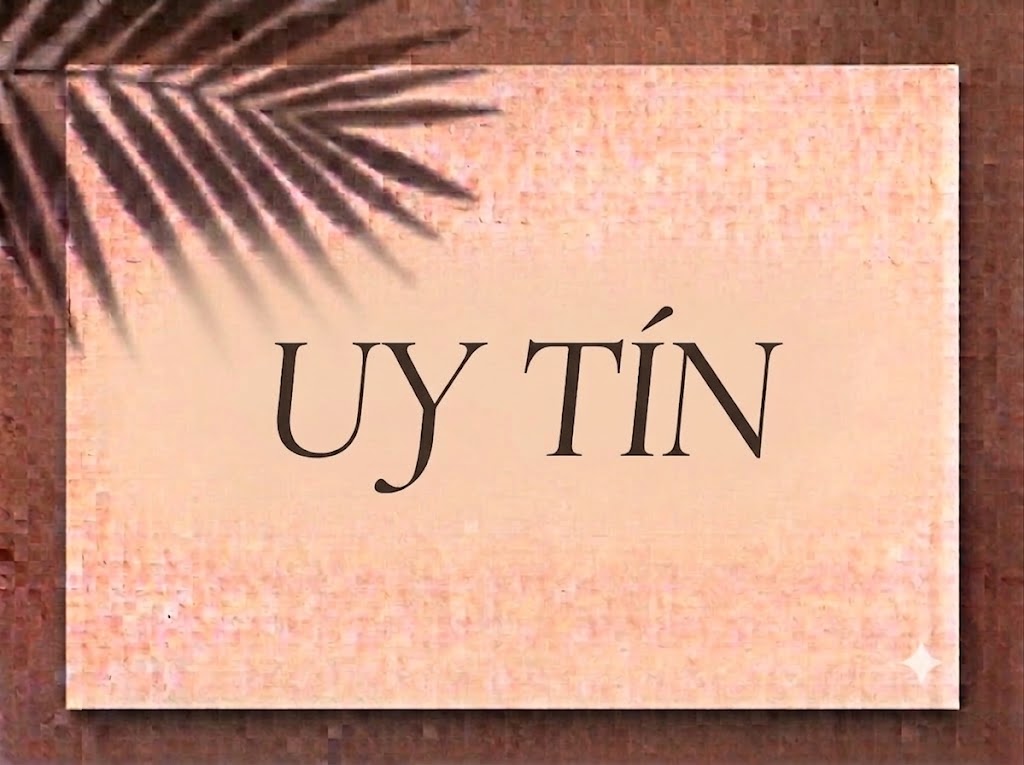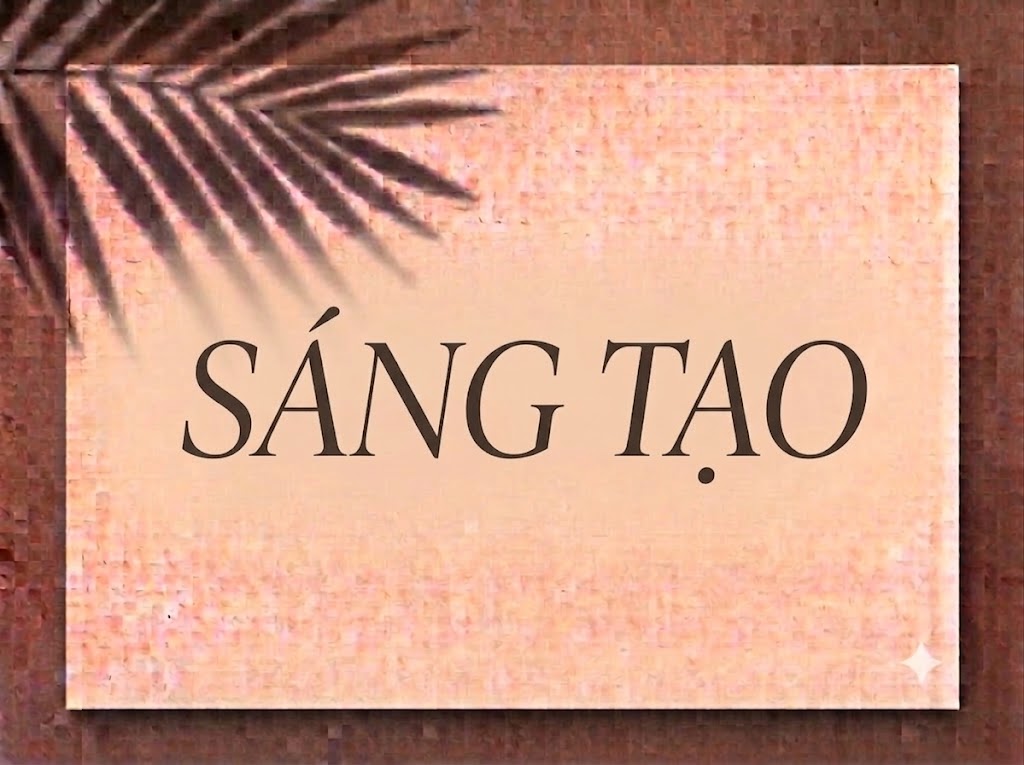
1FTV VIP Beauty Rovesa
Trong ngành thiết kế đồ họa cao cấp, các ấn phẩm thuộc lĩnh vực làm đẹp, spa, mỹ phẩm hay thời trang luôn đòi hỏi những phông chữ Serif sở hữu vẻ đẹp kiêu sa và đường nét tinh tế. Một tiêu đề được tạo hình đắt giá không chỉ giúp truyền tải thông điệp ngắn gọn mà còn ngay lập tức định vị thương hiệu ở phân khúc cao cấp.
Nếu bạn đang tìm kiếm một phông chữ hiển thị mang tinh thần sang trọng, kiều diễm với những nét uốn lượn mềm mại cho bìa tạp chí, logo spa hay tiêu đề video ngắn, font 1FTV VIP Beauty Rovesa chính là sự lựa chọn không thể bỏ qua.
Giới thiệu về font 1FTV VIP Beauty Rovesa
Font 1FTV VIP Beauty Rovesa là bộ chữ hiển thị có chân (serif display) mang phong cách tân cổ điển thanh lịch, nổi bật với sự kết hợp hài hòa giữa cấu trúc chữ Serif chuẩn mực và nét uốn lượn đầy tính nghệ thuật:
Tên phông chữ: 1FTV VIP Beauty Rovesa
Được tối ưu chỉn chu về mặt kỹ thuật, phông chữ đem lại khả năng hiển thị mượt mà trên mọi độ phân giải màn hình. Bạn có thể tự tin phóng lớn chữ trên các ứng dụng đồ họa chuyên nghiệp hay phần mềm dựng phim mà không lo gặp tình trạng vỡ nét hay răng cưa.
Đặc điểm nổi bật của phong cách thiết kế VIP Beauty Rovesa
Sức hút thị giác của font 1FTV VIP Beauty Rovesa đến từ vẻ đẹp mềm mại, quyến rũ cùng độ tương phản thanh đậm kịch tính:
Độ tương phản nét cực hạn: Sự chênh lệch rõ rệt giữa các cột dọc vững chãi và nét ngang mỏng nhẹ mang lại chiều sâu nghệ thuật, gợi liên tưởng đến trang bìa của các tạp chí thời trang và mỹ phẩm xa xỉ.
Nét biến điệu kiều diễm: Điểm nhấn đắt giá của phông chữ nằm ở các đường nét bo cong mềm mại ở các ký tự như e, g, f, a, T. Các chi tiết nét gạch ngang mảnh mai cùng phần đuôi uốn nhẹ giúp chữ mang lại cảm giác vô cùng nữ tính và thanh thoát.
Hỗ trợ chữ hoa và chữ thường đồng bộ: Phông chữ tích hợp đầy đủ hệ thống chữ cái viết hoa và viết thường, giúp các nhà thiết kế dễ dàng phối hợp để tạo ra nhịp điệu chữ thoáng đãng và tự nhiên.
Khoảng cách giữa các chữ (kerning) và độ giãn dòng được tính toán chuẩn xác, giúp các ký tự khi đứng cạnh nhau luôn giữ được khoảng trống thẩm mỹ lý tưởng, không dính nét hay rối mắt.
Tích hợp trọn vẹn bộ chữ cái hoa – thường, dãy chữ số 0-9 dáng đứng thanh lịch cùng hệ thống ký tự đặc biệt, dấu câu thông dụng.
Bản Việt hóa chuẩn chỉnh giúp bạn hoàn toàn yên tâm thiết kế các văn bản tiếng Việt có dấu mà không gặp lỗi nhảy font hay mất ký tự.
Hình ảnh demo thực tế của font 1FTV VIP Beauty Rovesa
Khả năng hiển thị của phông chữ này được tối ưu rất tốt trên nhiều tỷ lệ kích thước khác nhau:
Kích thước nhỏ (12pt – 24pt): Cấu trúc chữ đứng ngay ngắn và khoảng hở nội tại rõ ràng giúp bộ chữ thường và dãy số vẫn hiển thị sắc nét, ngay hàng thẳng lối trên màn hình di động.
Kích thước lớn (36pt – 72pt): Đây là đất diễn lý tưởng nhất để 1FTV VIP Beauty Rovesa phô diễn toàn bộ sự kiêu sa, quyến rũ của các đường nét thanh đậm và chi tiết biến điệu tinh tế, tạo tác động thị giác mạnh mẽ cho các dòng tiêu đề chính.
Ứng dụng trong thiết kế đồ họa và làm video
Sở hữu nét cá tính sang trọng và đầy tính thẩm mỹ, font 1FTV VIP Beauty Rovesa mở ra không gian ứng dụng phong phú:
Video ngắn (TikTok, Reels, Shorts): Phông chữ serif dáng kiều diễm này hiển thị rất đẹp trên khung hình đứng tỷ lệ 9:16. Nó cực kỳ ăn nhập với các video vlog phong cách sống, review mỹ phẩm, trang sức, spa hay thời trang nghệ thuật.
Ảnh thu nhỏ YouTube (Thumbnail): Lựa chọn tuyệt vời cho các kênh làm nội dung về làm đẹp, chăm sóc da, âm nhạc lofi, acoustic hoặc review đồ hiệu nhờ giao diện chuyên nghiệp và thu hút.
Thiết kế bìa tạp chí, Lookbook và Poster: Hoàn hảo cho các sản phẩm truyền thông thuộc lĩnh vực thời trang, spa, váy cưới, mỹ phẩm hoặc triển lãm nghệ thuật.
Nhận diện thương hiệu phân khúc Luxury: Thích hợp làm logo dạng chữ khối, menu nhà hàng hay khách sạn sang trọng, thiệp mời sự kiện VIP và bao bì nước hoa cao cấp.